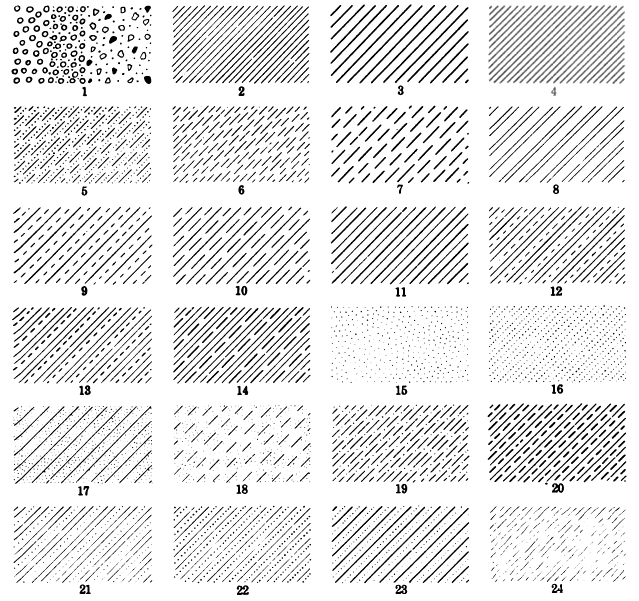
Inspiration gesucht: Schriften für einzeilige Etiketten für Lebensmittel/Gewürze/Tee
Unter dieser Voraussetzung kannst du deinen ganzen theoretischen Schnickschnack beseite lassen und einfach mal ausprobieren, wie ein paar der zahlreichen Vorschläge (die du auf einige wenige essentielle Unterschiede reduzieren kannst) wirken. Mehr wirst du mit einem Etikettendrucker nicht hinbekommen. Aber das ist in diesem thread ja nicht Neues.
Nun, ich habe das Merkmal 180dpi ja bereits früh im Thread erwähnt.
Dann haben offenbar mehrere Poster, die Laufweitenanpassungen vorschlugen, nicht bedacht, dass unter diesen Umständen, sowas nicht sinnvoll ist.
Bitte nicht als Kritik an denjenigen missverstehen.
Ich erwähne dies nur, um klarzustellen, dass ich die Rahmenbedingungen sorgfältig zusammengestellt hatte.
Selber habe ich kaum Erfahrung mit feinen Laufweitenanpassungen, weil ich das, besonders bei kleinen Schriftgraden, für etwas hielt, was man Experten überlassen sollte.
Als Laie, so dachte ich, ist die Gefahr groß, eher zu verschlimmern als zu verbessern.
… Als Laie, so dachte ich, ist die Gefahr groß, eher zu verschlimmern als zu verbessern.
Nicht, wenn man auf Ratschläge von Nicht-Laien hört.
Würdest Du sagen, dass ihr Profis in den allermeisten Fällen die Laufweite - und sei es auch minimal - anpasst?
Oder ist bei Versalhöhen von 4 mm Eurer Erfahrung nach kaum je eine Anpassung nötig?
Wir sprechen dabei von Gebrauchs- und nicht von Schmuckschriften.
Kommt drauf an ... wenn z.B. die Druckqualität schlecht ist, und ich sehe das nach den ersten Probedrucken, könnte eine Erweiterung der Laufweite nützlich sein, die Buchstaben besser voneinander getrennt zu halten - insbesondere bei Schriften, die vom Gestalter eher eng zugerichtet wurden (das unterliegt übrigens auch eindeutig Trends) ... oder wenn ich den Text senkrecht setze, hilft eine Laufweitenerhöhung beim Lesen ... ebenso wenn ich weiß auf schwarz drucken will. Das steht auch alles in "systematisch" vorgehenden Lehrbüchern so drin, und ist natürlich vorerst auch mal "richtig", solange die Praxis nicht eine Korrektur einfordert.
Schwarz auf weiß, waagrecht, bei guten Lichtverhältnissen, auf normalem Papier bei Offset-Qualität, bei einer "typisch" zugerichteten Schrift kannst du bei 4mm Versalhöhe (ca 11,5pt) die Laufweite vermutlich vorerst mal unverändert lassen, bis beim Betrachten der ersten Testmuster erkennbar wird, dass eine Änderung vielleicht gut tun könnte.
Sowas hilft mir weiter - auch deutlich über das Thema dieses Threads hinaus.
Darf ich um Eure Ansicht zu den Proportionen des Weißraums bitten?
Ausgeglichen wirkt's, wenn der Weißraum unten etwas größer ist als oben. Steht auf einer weißen Fläche ein Strich genau in der senkrechten Mitte, wirkt er, als sitze er etwas zu tief. Rückt man ihn etwas nach oben, wirkt es ausgeglichener und stabiler.
Da Unterlängen seltener vorkommen und oft sogar noch kürzer sind als Oberlängen, hat man unter der Schrift mehr Weißraum als darüber. Unten ist ja etwas mehr Weißraum erwünscht, aber der Unterschied ist fast immer zu stark, sodaß man die Schrift etwas nach unten versetzen muß.
Hier ein Beispiel. Die Zeile ohne Ober- und Unterlängen sieht ausgeglichen aus, wenn unten ein Tick mehr Weißraum ist als oben:
Mit Ober- und Unterlängen sitzt die Zeile dann aber zu hoch:
Um einen guten Mittelwert zu finden, kommst Du nicht darum herum, einige Beispielwörter auszudrucken und zu beurteilen.
Mich interessiert noch Eure Gewichtung des Kriteriums "Eindeutigkeit von Buchstaben" (Bsp. Großes I, kleines L).
Ich halte das für ziemlich unwichtig in Deinem Fall. Aus dem Zusammenhang ist eigentlich immer klar, was gemeint ist (weil beispielsweise ein großes I in der Wortmitte gar nicht vorkommen kann). Auch die Unterscheidung von r-n zu m oder i zu l ist bei normalen Lesebedingungen (nicht zu dunkel, kein reflektierender Untergrund oä.) nach meiner Erfahrung unproblematisch.
Meine etikettierten Gewürzgläser haben in den Jahren schon etliche meiner Freunde zum Nachahmen inspiriert :)
Nun werde ich bald für eine Freundin Etiketten ausdrucken. Leider konnte ich sie nicht davon überzeugen keine fertig gemahlenen  Gewürzen zu verwenden :)
Fällt euch eine hübsche Darstellung der Eigenschaft "gemahlen" ein?
Ich denke im Moment an die Darstellung von Gelände in Landkarten.
Zum Beispiel 15. Oder 1 rechter Teil.